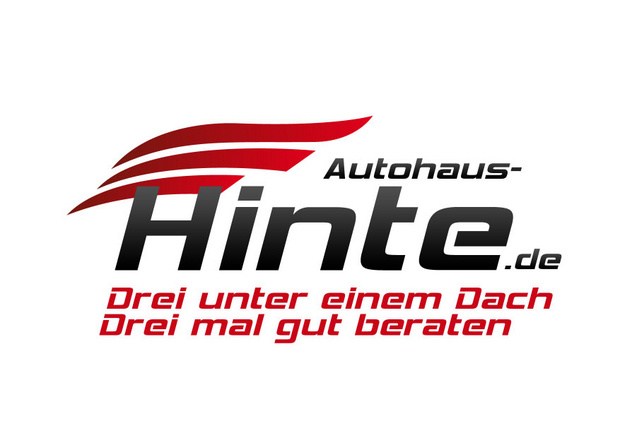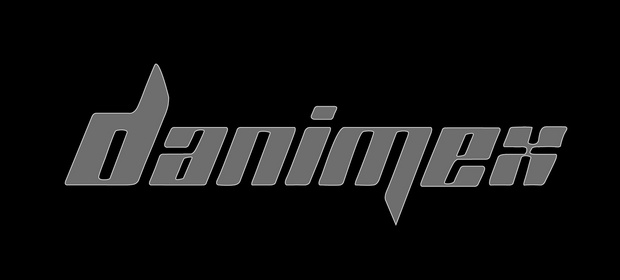
Habe 2 Schriftprobleme :-(
Habe 2 Logos wofür ich die Schrift nicht finden kann. Hat von Euch einer eine Idee?
Den gibt es auch (legal?) bei diversen Freefontseiten als Hemi Head 426 … verzerrt ist er jedenfalls auch noch. Genauso wie "Planet Kosmos", die Grundlage für danimex.